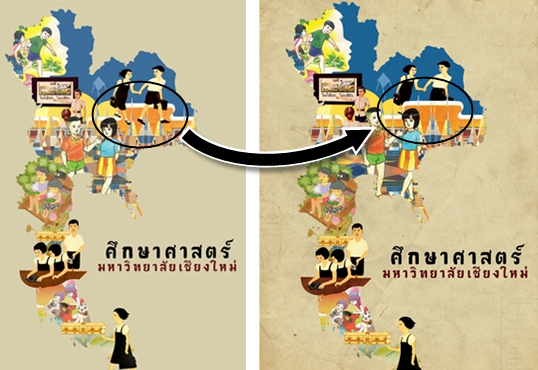
มานี มีใจ แสดงงาน
อ่ะ แบบที่หนึ่งสีน่ารักสดใสมากๆๆ ผู้หญิงคงจะชอบเลยล่ะ
แบบที่สองดูได้อารมณ์สมัยวัยเด็ก
แบบที่สามก็เท่ดีนะ ดูเซอๆดี รวมพวกแบบเรียนใช่มั้ย
ชอบอันที่ 1 กับอันท ี่3 ล่ะ โลภอีก ฮ่าๆ  :02:
มาแก้ไขค่ะ
สรุปมีทั้งหมด 5 แบบ จากการประมวลผล เซ็ต1 กับ เซ็ต2
และ ได้ผลออกมาดังนี้  :01:
แบบที่1
แบบที่2
แบบที่3
แบบที่4
แบบที่5
ภาพรวม  :37:
รบกวนโหวตอีกทีนะ โหวตได้ 1-3 อัน
งั้นเอา 1 ,3 แล้วก็ 4
อันสุดท้ายก็ดูดีนะ
รูปที่สองนั่นแหละดีอยู่แล้ว
เจ้ารูปแรก เด็กมันเหมือนเหยียบยอดเจดีย์อยู่ ดูแล้วไม่เหมาะเท่าไหร่อะ
ตอนแรกจะมาเตือน แต่เห็นรูปที่สองแก้แล้ว ก็เลยสบายใจ...
ปล.ชอบ 1,5